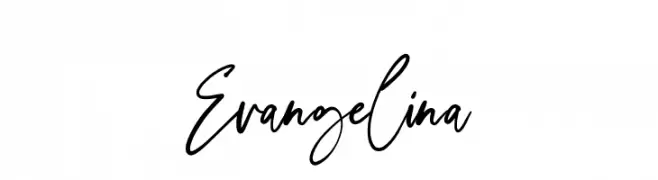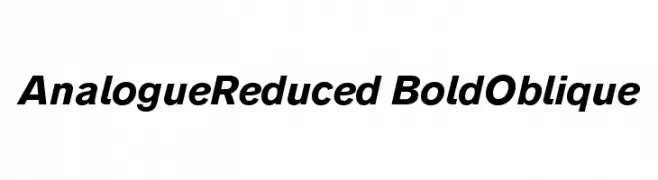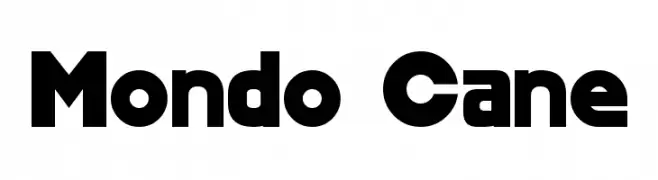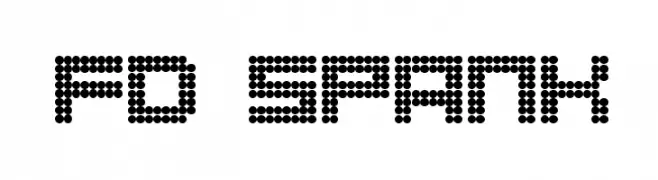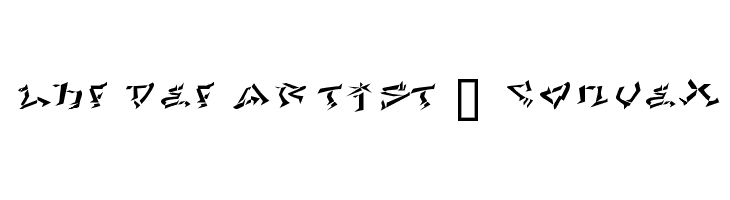
Добро пожаловать в раздел Топ шрифтов — здесь популярность встречается с качеством. Это самые скачиваемые и используемые шрифты нашего сообщества за этот год. Если нужны надежные варианты для логотипов, сайтов или соцсетей — начните отсюда.
Каждый топ‑шрифт отличается балансом, читабельностью и универсальностью. Здесь есть современные гротески, изящные скрипты, винтажные антиквы и минималистичные дисплейные семейства. Если не знаете, с чего начать, раздел «Топ» — ваш короткий путь к проверенной типографике.
A bold, distressed font with a gritty, industrial texture.
A bold, dynamic font with sharp, jagged edges and a sense of movement.
A dynamic and expressive handwritten font with fluid cursive letterforms.
A bold, oblique sans-serif font with a modern and assertive style.
A bold, calligraphic font with dynamic strokes and artistic flair.
A bold, italicized font with smooth, rounded strokes and an extended form.
A bold, geometric font with a strong, modern presence.
Какие шрифты в топе прямо сейчас?
Дизайнеры любят Summon the Executioner Regular, EpicSlash, Evangelina, AnalogueReduced-BoldOblique and The Black Pearl за чистые формы и широкий спектр применения — от фирменного стиля до лендингов и постеров.